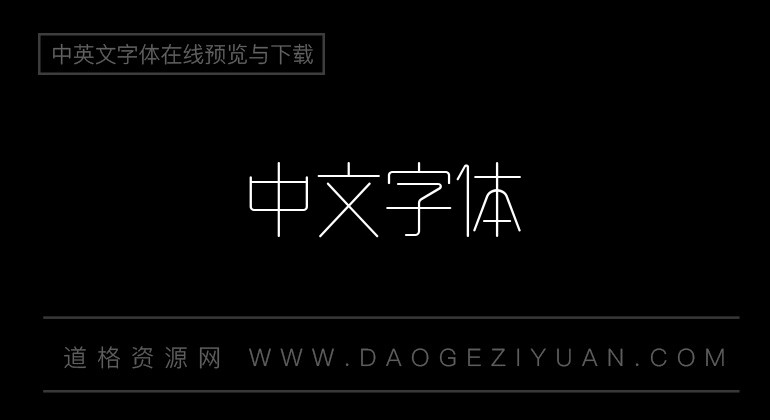
? 造字工房云川体是一款由造字工房推出的中文字体,它采用了自然的线条和曲线,拥有舒适的字形,十分适合用于报纸、杂志、书籍等出版物的设计。它的字形细腻精致,是最适合用于中文文字设计的字体之一。文件名:ZaoZiGongFangYunChuanTi-2.ttf
造字工房云川体是一款非常不错的手写艺术字体,具有很好的视觉感,适合于文化类的宣传设计、商业类品牌的广告和产品包装设计以及个性化文字排版等较多场景。